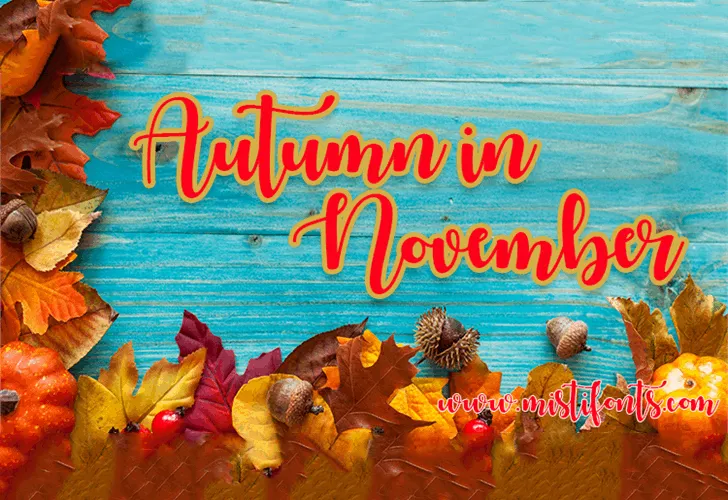
Autumn in November Font – Download Grátis
A autêntica Autumn in November Font foi criada pelo designer Misti’s Fonts com um estilo fresco e suave que evoca a atmosfera misteriosa do outono no natal, oferecendo letras cuidadosamente escritas que transmitem uma sensação de tranquilidade. Suas linhas delicadas e detalhes finos permitem criar texturas intrigantes sem perder a elegância necessária para qualquer projeto gráfico. Este tipo de fonte é perfeito para anúncios, cartões de natal ou até mesmo o design de sites para empresas que valorizam um toque personalizado em seus materiais digitais. Com sua aparência encantadora e versátil, Autumn in November Font está mais do que equipada para complementar qualquer projeto gráfico no qual você possa usá-la.